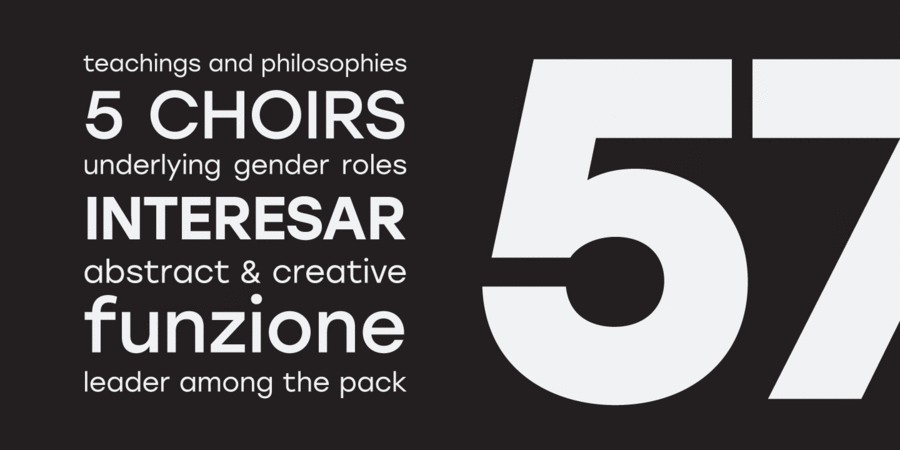
Stolzl Text є доповненням до шрифтового сімейства Stolzl Display від The Northern Block. Він був спеціально розроблений як більш функціональне доповнення. Stolzl Text – інтерпретація першого акцидентного шрифту, позбавлена основних стилізованих атрибутів, тому вона добре читається на паперових носіях та на екрані. Stolzl Text – відмінне доповнення до колекції шрифтів для роботи на різних сайтах. Поряд з латинськими мовами ця гарнітура також підтримує кирилицю, включає шість насиченостей, 486 символів, відредагований вручну кернинг і функції Opentype. Шрифт розробила Марія Пігулевська у 2015 році. Stolzl™ є торговою маркою компанії The Northern Block.
Хіт 1920-х Хіт 1930-х Хіт 2010-х Stolzl Text підтримує 83 мовиУкраїнська, Англійська, Німецька, Польська, Португальська, Іспанська, Французька, Російська, Чеська, Голландська, Італійська, Шведська, Турецька, Фінська, Білоруська, Сербська, Болгарська, Естонська, Литовська, Албанська, Африкаанс, Баскська, Бретонська, Валенсаска, Galician, Гельська (Шотландська), Данська, Індонезійська, Ірландська, Ісландська (Win), Каракалпацька, Каталонська, Норвезька, Окситанська, Ретороманська, Самі Лулі, Тсванська, Узбецька (Лат.), Фарерська, фризька, Чаморро, Естонська (Win), Південносаамська, Албанська (Win), Угорська, Верхньолужицька, Карельська, Латвійська (Mac), Литовська (Mac), Маорійські (Mac), Молдавська (Лат.), Нижньолужицька, Румунська (Win), Словацька, Словенська, Туркменська (Лат.), Хорватська (Win), Естонська (Mac), Курдська, Латишська, Маорійські, Руминська, Абазинська, Аварська, Агульська, Адигейська, Даргинську, Інгуську, Кабардино-Черкеська, Кабардинська, Карачаєво-Балкарська, Кумицька, Лакська, Лезгинська, Македонську, Мордовсько-Мокшанська, Мордовсько-Ерзянська, Ногайська, Рутульська, Табасаранська, Татська, Цахурська, Чеченська Функції сімейства шрифтів Stolzl TextЗастосування гарнітури у верстці:
Асоціації з сімейством шрифтів Stolzl TextОсобистість і характер гарнітури:
елементарний, мінімалістичний, точний, рівний, статичний, логічний, лаконічний, стійкий, автоматичний, штучний, холодний, інженерний, міський, різкий, чіткий, креслярський, чистий, сучасний, гострий, тонкий, дротяний, скляний, легкий, прохолодний, ясний, невагомий, прозорий, крихкий, модний, неоновий, худий, твердий, сталевий, Простий, машинний, крижаний, надійний, впевнений, урбаністичний, технічний, стабільний, нейтральний, серйозний, переконливий, залізний, мужній, індустріальний, техногенний, армійський, грубий, мотивуючий, амбітний, жорсткий, важкий, авторитетний, значний, гучний, сильний, важливий, монументальний, крутий, практичний, міцний, формальний, залізничний, зрозумілий, солідний, самостійний, відповідальний, добротний, архітектурний, кондовий, прямокутний, суворий